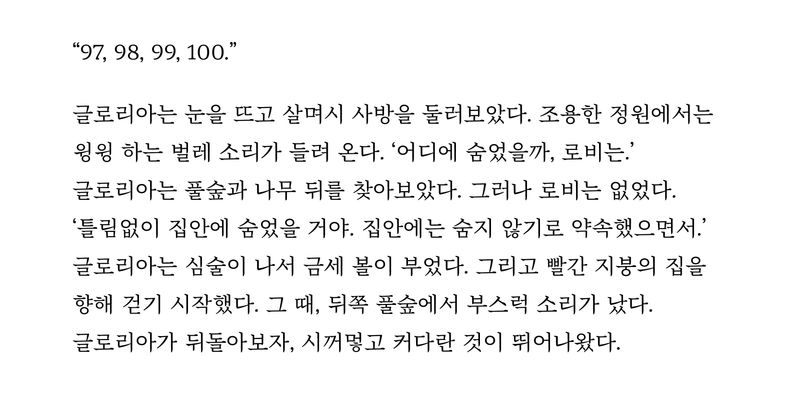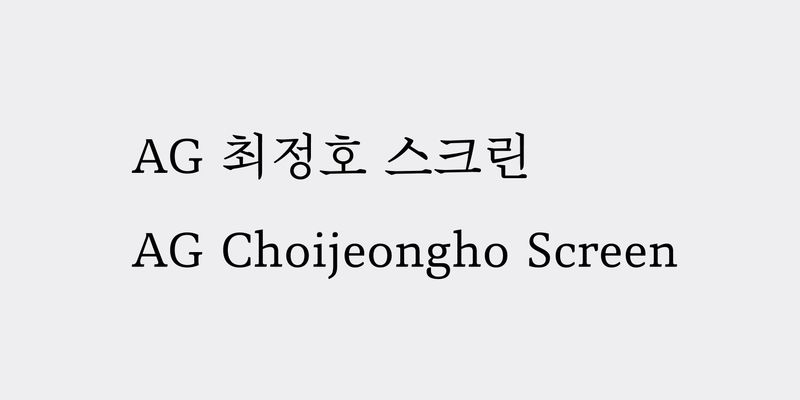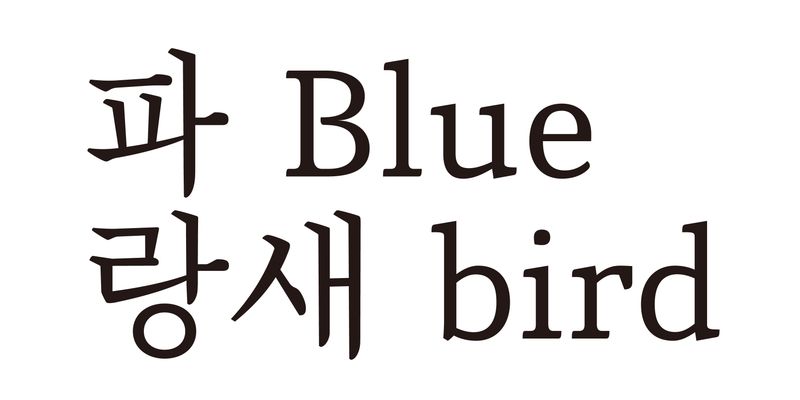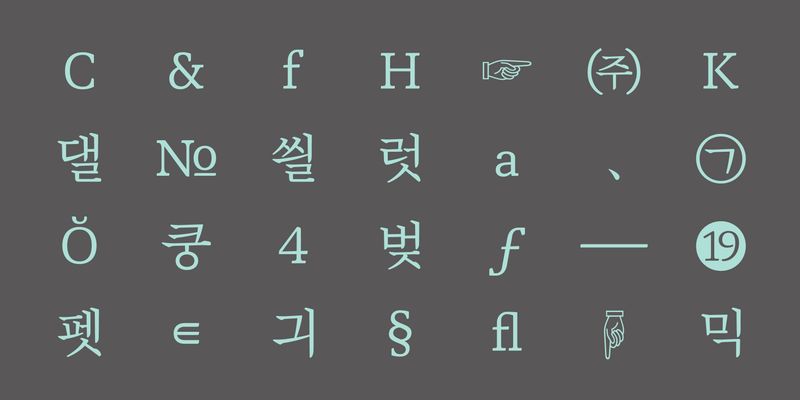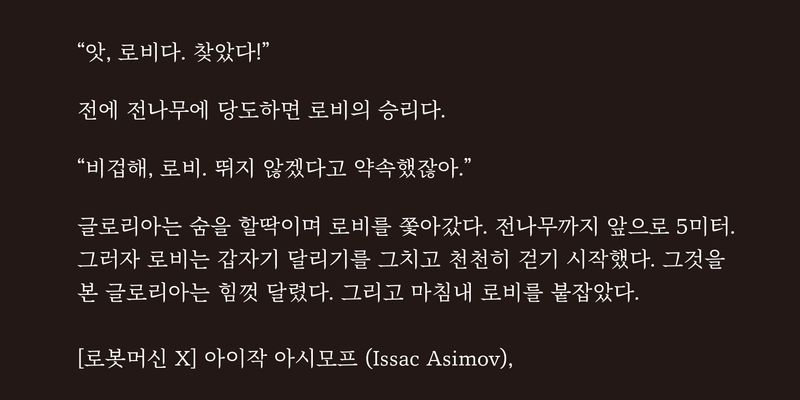
「Choieongho」は、ハングル書体デザイナーの Choi Jeongho がデザインしたセリフ書体です。このデザインは 1988 年に Ahn Sang–soo から依頼されたもので、Choi Jeongho の死後に彼の一連の原画が発見されました。当社は、2017 年に、これらの原画に基づいて「AG Choijungho Std」書体を開発しました。 「AG Choijungho Screen」は、「AG Choijungho Std」をベースに、画面上で歪みなく表示されるように、字形やバランスが調整されています。 ブリ体と線の終端部の形をシンプルにするとともに、横画と縦画の太さが同じに見えるようにしました。「AG Choijungho Std」よりも形はシンプルですが、上品な印象は変わらないよう調整しています。 ハングルと同様、ラテン文字も「AG Choijeongho Std」をベースに画面上で歪みが出ないように改良されました。またマルチスクリプト環境で相互の文字を補完して調和するようにデザインされています。 「AG Choijeongho Screen」は、2,574 のハングル文字、296 のローマン体と拡張ローマン体、776 の約物で構成されています。